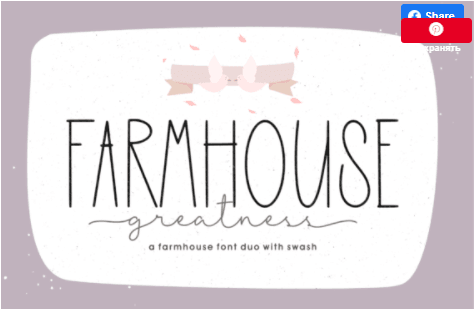
Farmhouse Greatness Font
Farmhouse Greatness состоит из двух шрифтов, идеально дополняющих друг друга. Вместе или по отдельности эти шрифты идеально подходят для придания шикарного и радостного оттенка вашим поделкам. Этот шрифт имеет кодировку PUA, что означает, что вы можете легко получить доступ ко всем глифам и росчеркам!